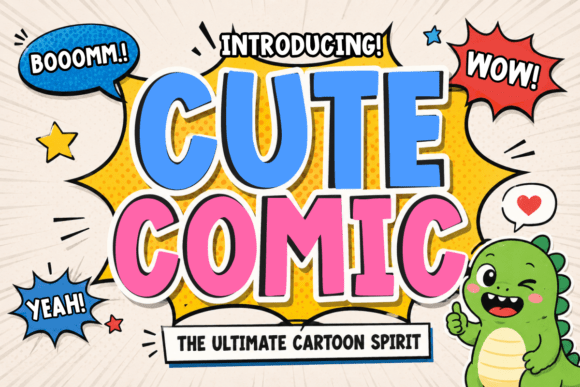
Cute Comic
Encontrar los elementos de diseño adecuados puede ser un desafío, pero Cute Comic ofrece una colección excepcional que eleva tu trabajo al instante.
Elaborado con precisión, Cute Comic proporciona vectores limpios, tipografía suave y una licencia comercial para tu tranquilidad.